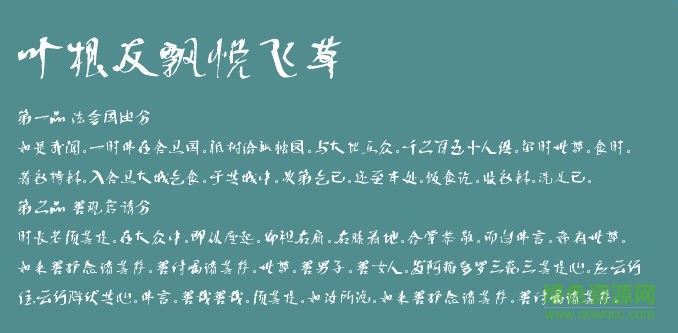
葉根友飄悅飛草字體是一款美觀的葉根友手寫字體,該字體筆勢連綿,形體飄逸,瀟灑暢達(dá),十分具有動態(tài)美,可應(yīng)用于各類藝術(shù)設(shè)計(jì)方面,喜歡的朋友快來綠色資源網(wǎng)下載吧!
葉根友飄悅飛草字體是一款手寫字體,字體筆畫看起來眉飛色舞,但是極具連貫性,筆畫行云流水,突出手寫的藝術(shù)特色。該字體適用于廣告設(shè)計(jì)、藝術(shù)設(shè)計(jì)等方面,需要的話可以來下載使用。
葉根友飄悅飛草字體線條靈動灑脫,字形不拘一格,十分好看,制作創(chuàng)意字體、廣告宣傳、海報設(shè)計(jì)等都用得上!